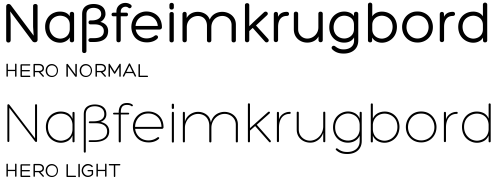
Die besten Freeware-Fonts
Die Schriftschmiede Our Type von Fred Smeijers bietet bis 31. Mai folgende Schriftschnitte zum kostenlosen Download an:
• Meran Light Std
• Meran SemiBold Std
• Meran SemiCondensed SemiBold Std
• Meran SemiCondensed SemiBold Italic Std
• Meran Condensed Thin Std
• Meran Condensed Black Std
• Eva Semibold Std
• Eva SemiBold Italic Std
• Fayon SemiBold Std
• Fayon SemiBold Italic Std
Much sought-after at the TYPO-Design Conference 2011 in Berlin: the font stencil FontFummler Pro. The stencil provides all the necessary modules to construct a small letter alphabet in a few minutes or to fumble a whole word together. The gimmick was designed by Lars Krueger, his colleague Alexander Roth designed the perfect sample alphabet: Fummel. It comes, for the impatient font lovers among us, packed in an OpenType Font and is available for free. With Fummel you can easily fumble around on your computer!
Dieter Hofrichter, langjähriger Assistent von Günter Gerhard Lange, veröffentlicht seit kurzem Schriften unter eigenem Label: Hoftype. Bei MyFonts bietet er derzeit die Light-Schnitte seiner Schriften Cala und Erato für 0 € an.
Cala is a reflection of Venetian Renaissance types but with a contemporary look. It has an energetic profile, achieved through soft outlines and a flowing rhythm. It is lively, remains stable in small sizes and is beautiful in display sizes.
Cala comes in eight styles, in OpenType format and with extended language support. All weights contain standard and discretional ligatures, small caps, proportional lining figures, tabular lining figures, proportional old style figures, lining old style figures, matching currency symbols, fraction- and scientific numerals.
Erato follows the structure of french and dutch 17th century types. But instead of being historical, it uses modern formal elements. The simplification of similar formal elements creates a homogeneous and contemporary impression.
Erato comes in six weights and in OpenType format.
All weights contain standard and discretional ligatures, small caps, proportional lining figures, tabular lining figures, proportional old style figures, lining old style figures, matching currency symbols, fraction- and scientific numerals.
Von der Erato bin ich richtig begeistert: Eine zeitgemäße, aber dennoch sehr klassische Neuinterpretation. Für mich ist das die neue Garamond!
Ich mag das Plantin „a“ in Erato. Gibt es zu der Schrift irgendwo ein PDF-Specimen?
Auch ein schönes Beispiel wie man ein kleines „f“ gestalten kann, welches beides, mit geschwungenem Bogen, und nicht im Konflikt mit den Umlauten ist. Was auch erfreulich ist, dass jeder Buchstabe etwas Charakter hat, die Schrift fühlt sich nicht an, als ob zu viele Linien einfach nur kopiert wurden. Einige der jüngeren Serif-Schriften haben manchmal diesen Mangel, kommt vielleicht weil sie nicht mit der Hand vorskizziert wurden? Jedenfalls langweilen mich manche Schriften die mir zuerst gefalllen, weil sie zu gleichmäßig sind, wodurch man sich im Schriftbild an nichts festhalten kann.
Ist zwar schon etwas älter, aber ich hab sie eben erst zufällig entdeckt: Die kostenlose Hero von Fontfabric.
Du bist doch hier der ß-Ästhet. Sag bloß, dass du gerade dieses ›ß‹ schön findest :-o
Nein. Ich finde es einigermaßen akzeptabel. Du mußt aber zugeben, daß es so einen netten Chinesische-Betriebsanleitung-mit-Betas-Charme versprüht. :lol:
Bei Linotype gibt es diesen Monat die Akko von Akira Kobayashi kostenlos
Das sind aber keine Freeware-Fonts. :-)
P.S. Ich hatte deinen post nicht gesehen, drum hab ich’s nach dir in "Veröffentlichungen" gepostet.
Freeware ([ˈfɹiːˌwɛə]; von engl. free „kostenlos“ und ware „Ware“) bezeichnet im allgemeinen Sprachgebrauch Software, die vom Urheber zur kostenlosen Nutzung zur Verfügung gestellt wird. Freeware ist meistens proprietär und darf daher nicht mit freier Software (engl. „free software“) verwechselt werden, die im Gegensatz zu Freeware weitläufigere Freiheiten, wie Veränderungen an der Software, gewährt.
Ich persönlich verwende Linux Libertine.